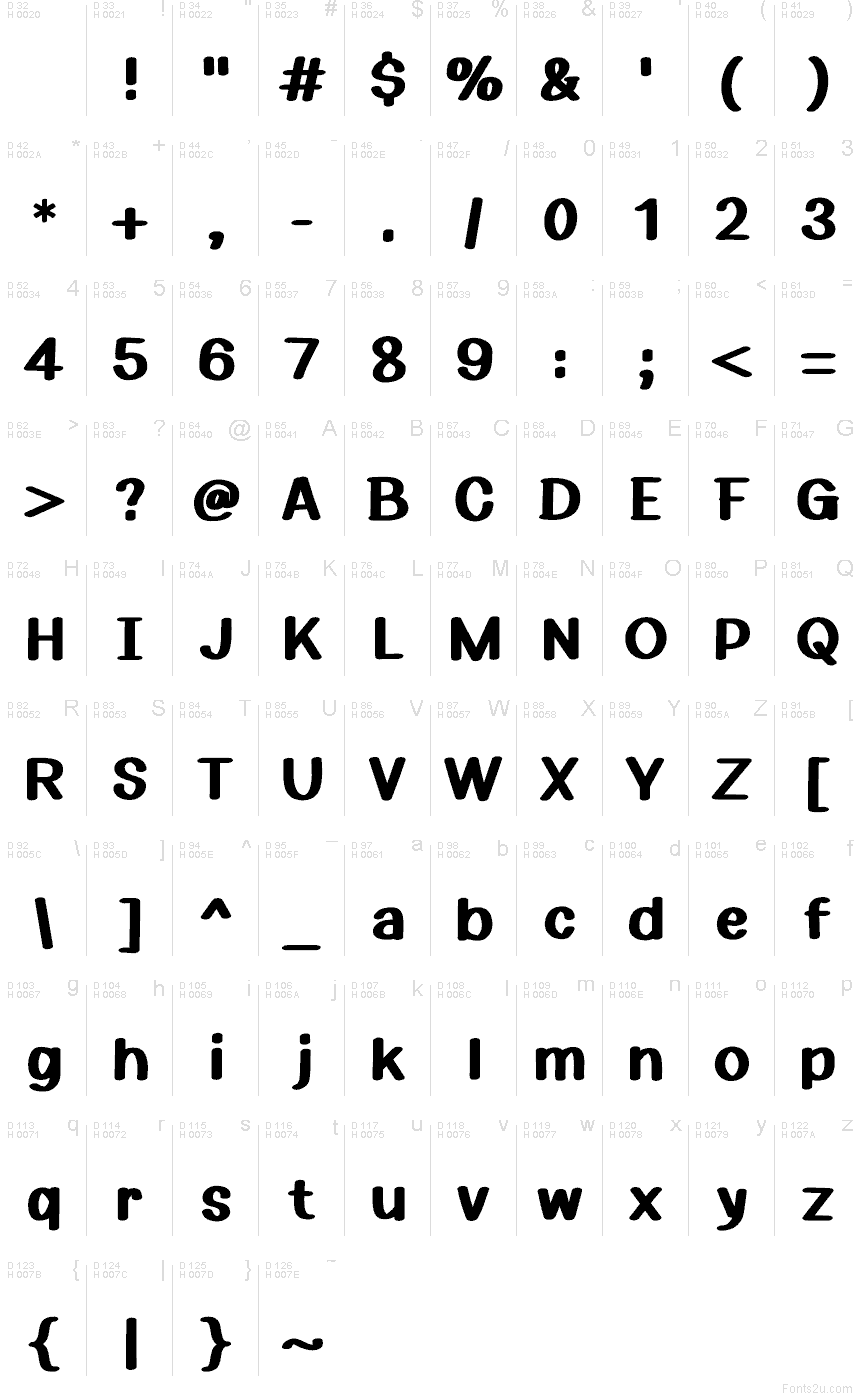
Funny Hello від Hello Good Studio - це безкоштовний акцидентний шрифт у коміксному стилі з округлими, намальованими від руки літерами та м'якими, нерівномірними вигинами, що надають йому дружній і невимушений ритм. Форми виглядають живими, а не жорсткими, завдяки плавним переходам і злегка звуженим кінчикам, які позбавляють літери механічного вигляду.
Funny Hello чудово підійде для дитячих плакатів, листівок, ігрових логотипів, афіш заходів, графіки для соцмереж та пакування, де потрібен легкий і неформальний тон. Ці округлі форми добре виглядають у коротких фразах і декоративних заголовках, де розслаблена структура шрифту додає чарівності ручного письма, не втрачаючи при цьому читабельності.